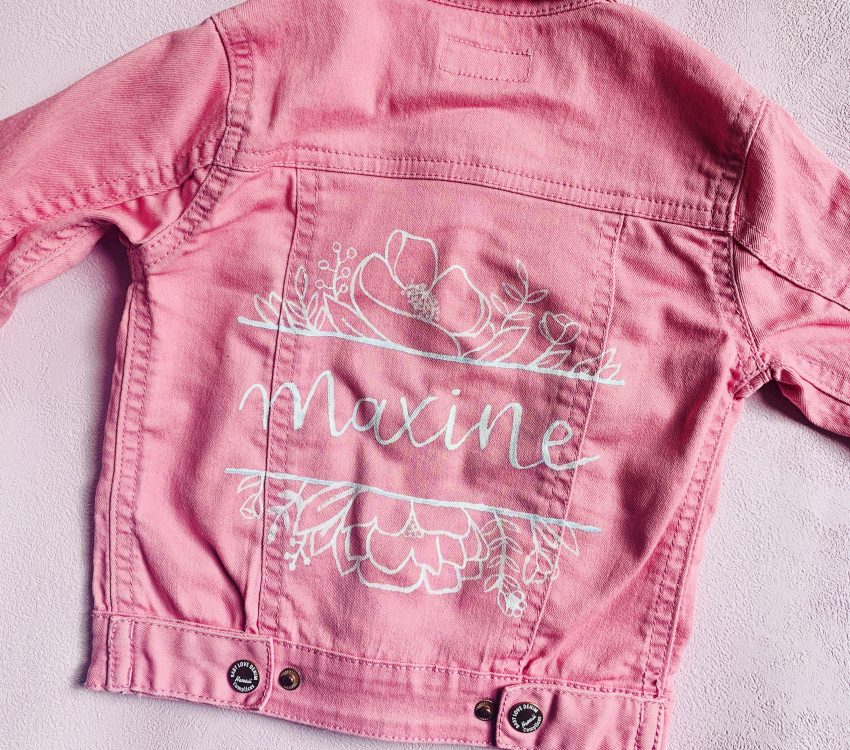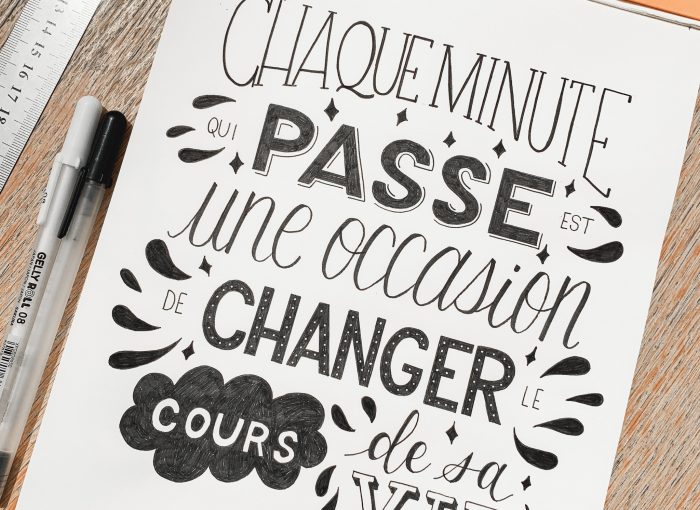
Je suis spécialisée dans le dessin et l’écriture des 26 lettres de l’alphabet. Je m’inspire souvent de citations positives pour créer des illustrations pleines de couleurs et d’énergie.
Ma mission est d’utiliser l’art pour inspirer et faire sourire les autres. J’utilise la signification et la forme des mots pour créer des lettrages uniques, alignés avec les valeurs et l’identité de mes clients !